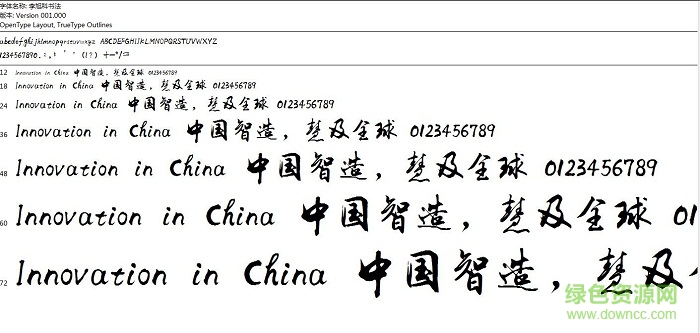
李旭科草书字体
李旭科草书书法字体是一款笔势连绵的草书字体,该字体气势雄健,饱满张扬,线条如如行云流水,奔逸洒脱,一气呵成,极具吗,美感,用在小伙伴们赶紧下载吧!
草书发展特点
初期的草书,打破隶书方整规矩严谨,是一种草率的写法。称为“章草”。章草是早期限草书和汉隶相融的雅化草体,波挑鲜明,笔画钩连呈“波”形,字字独立,字形遍方,笔带横势 。章草在汉魏之际最为盛行,后至元朝方复兴,蜕变于明朝。